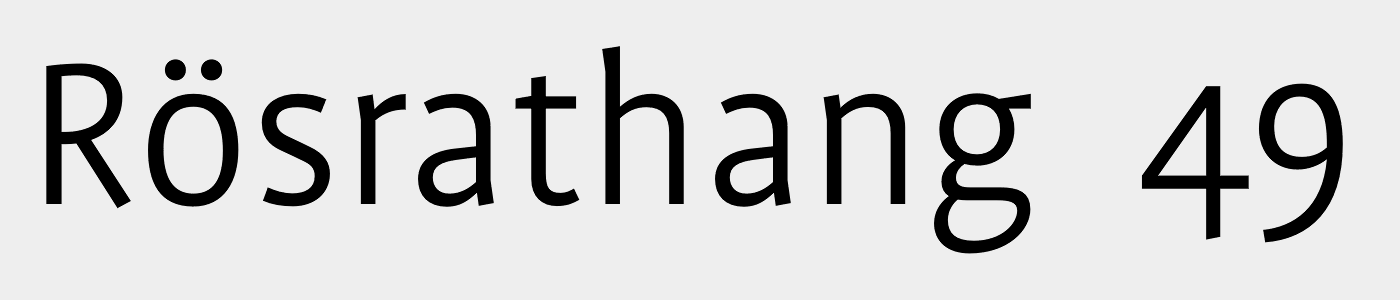
Schrift ähnlich Akagi Pro
Kann mir jemand bei der Identifizierung helfen? Die Akagi Pro ist es nicht, Alber new auch nicht ...
Ist das ein Scan? Ein Screenshot? Woher stammt er? Gibt es mehr als nur diese Zusammenstellung?
Ja, ist ein Scan eines Teiles eines Briefbogens. Mehr gibt es leider nicht ....
So ein @ hatte ich vorher noch nie gesehen …